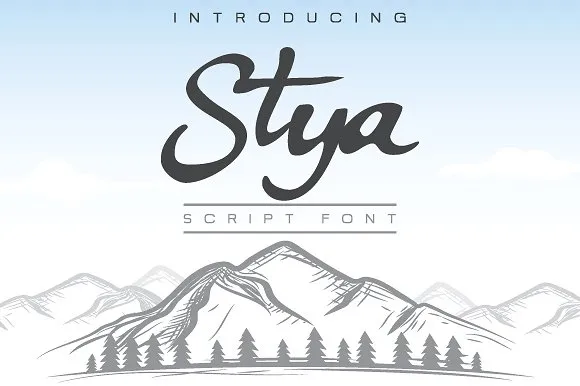
Stya Script Font – Fonte Grátis
Stya Script Font
A Stya Script é uma nova opção para quem busca uma fonte elegante e sofisticada para seus projetos gráficos. Lançado pelo designer menangan studio, a Stya Script está aqui para atender as necessidades de criatividade que seu trabalho requer. Esta fonte única se destaca como um script perfeito para aplicação em logos, cabeçalhos, rótulos e headlines, além de ser uma ótima escolha para o desenvolvimento de marcas. Oferecida no formato otf e ttf, a Stya Script está pronta para adicionar um toque especial ao seu próximo projeto. Com sua graça e sutileza, a Stya Script se destaca como uma opção ideal para qualquer aplicação que exija elegância e estilo. Ideal tanto para designers profissionais quanto iniciantes que desejam explorar novos recursos em suas criações digitais.